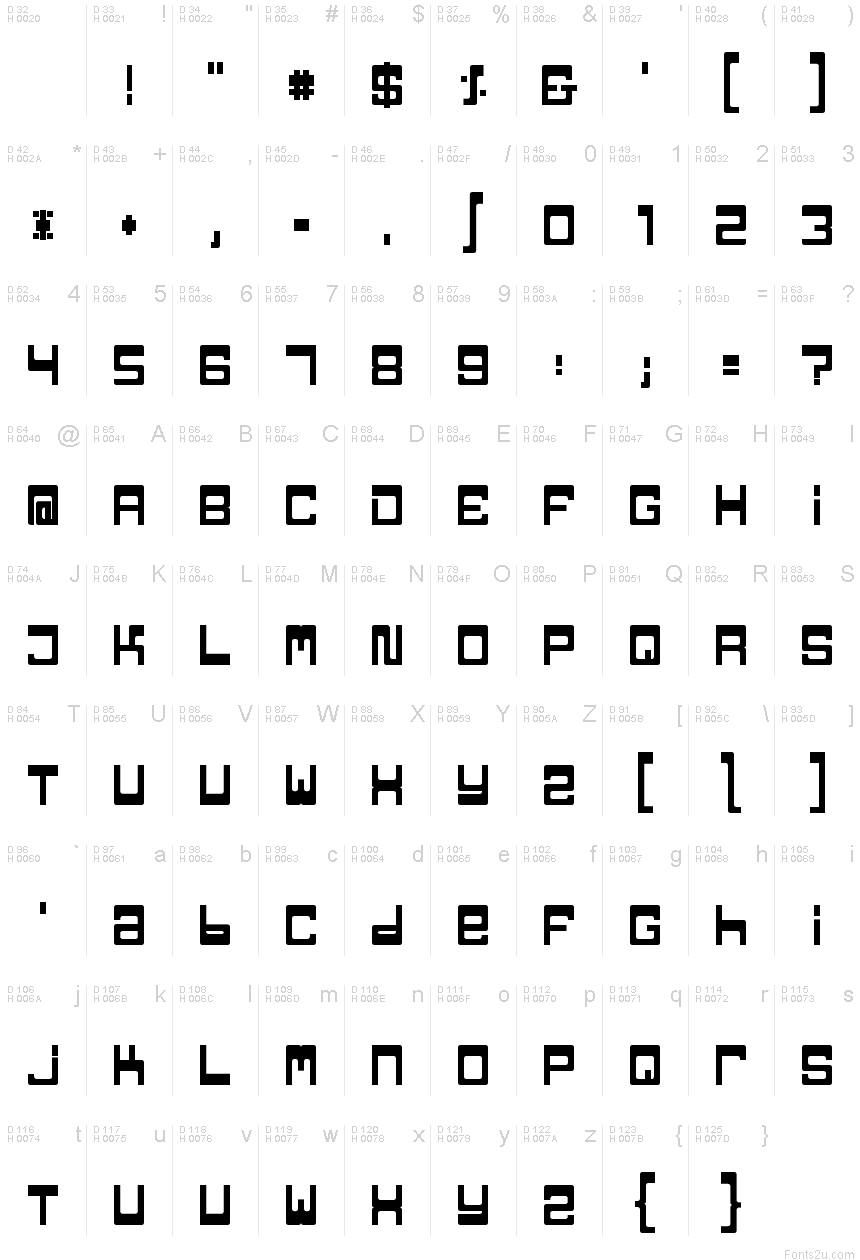
TPF Jaib Bold, autorstwa Christopha Scheiblhofera, to darmowy, utrzymany w stylistyce retro-techno krój typu display, z wyraźnym, arkadowym pulsem. Litery zbudowane są z ciężkich, prostokątnych form i wyciętych detali, co nadaje krojowi kompaktowy, modułowy rytm, przywodzący na myśl wczesne gry wideo i elektronikę lat 70.
Naturalnie sprawdzi się na plakatach, okładkach płyt, klubowych ulotkach, planszach tytułowych i opakowaniach, wszędzie tam, gdzie potrzebny jest blokowy, futurystyczny akcent. Jako darmowy font, doskonale nadaje się również do nagłówków i krótkich logotypów – kwadratowe narożniki i precyzyjne wycięcia nadają nawet krótkim tekstom solidną, maszynową prezencję.
TPF Jaib